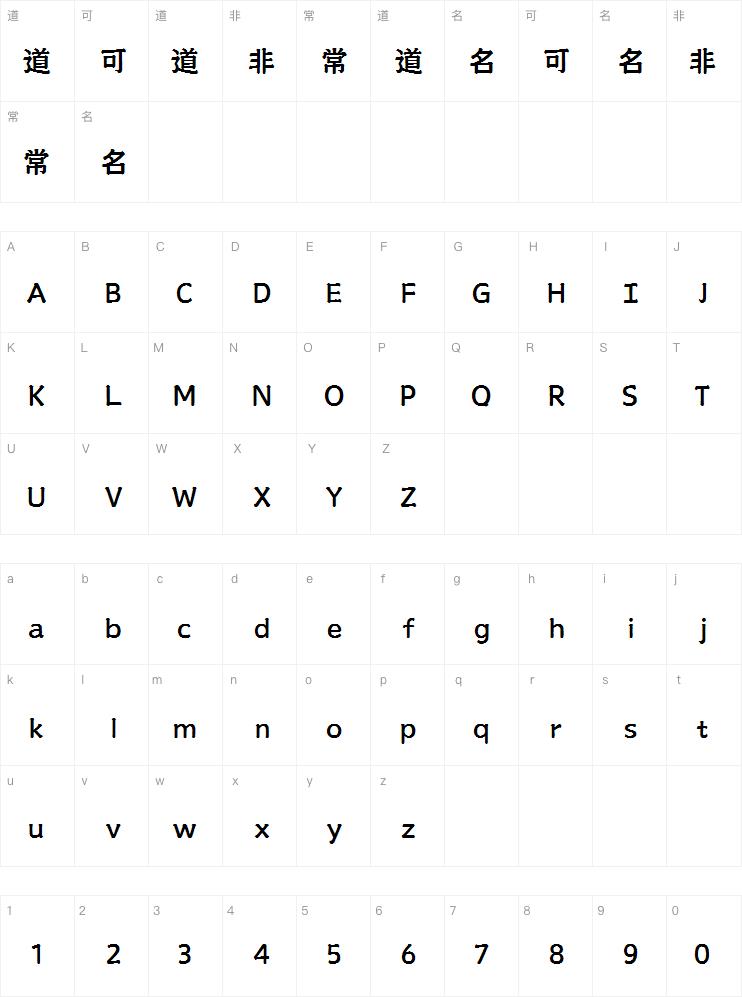
山海国潮 65w
山海国潮65W,是一款全新的字体,是山海国潮字体家族系列中的常规粗细款,编号65W,包含汉字9169个,符号200+个。该字体雄健有力,非常醒目!融入榜书特点,有力、宽厚、方正,如同巍峨的大山,充满了稳重感和设计感。笔画与字形间透露着古雅和刚劲的特点,在古朴的同时而又极富张力,桀骜不驯的特性,霸气外露。它的笔画充满力量感,组合搭配极富强烈的节奏感。在粗细的纵横间,拥有非常规的张力特性。
山海国潮 65w